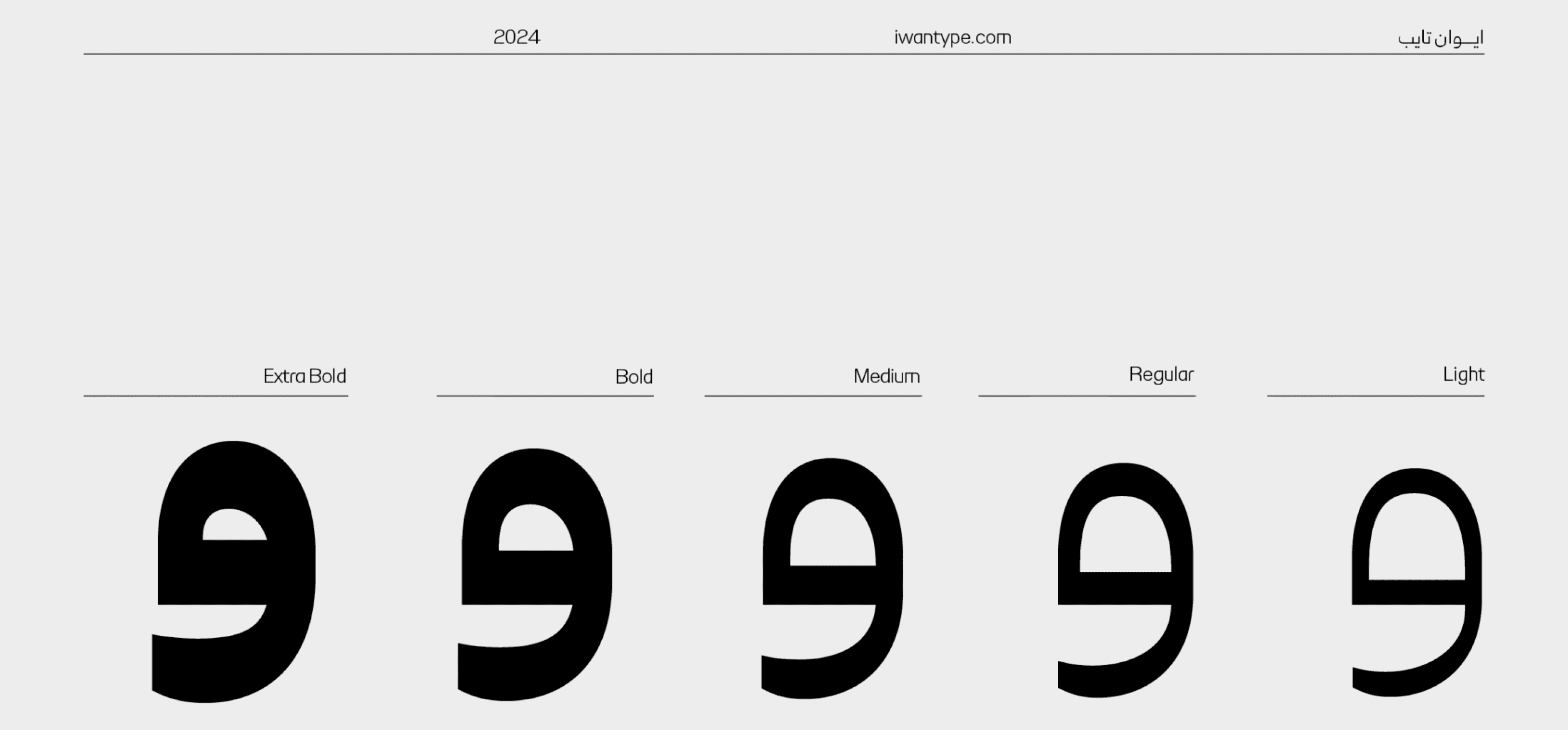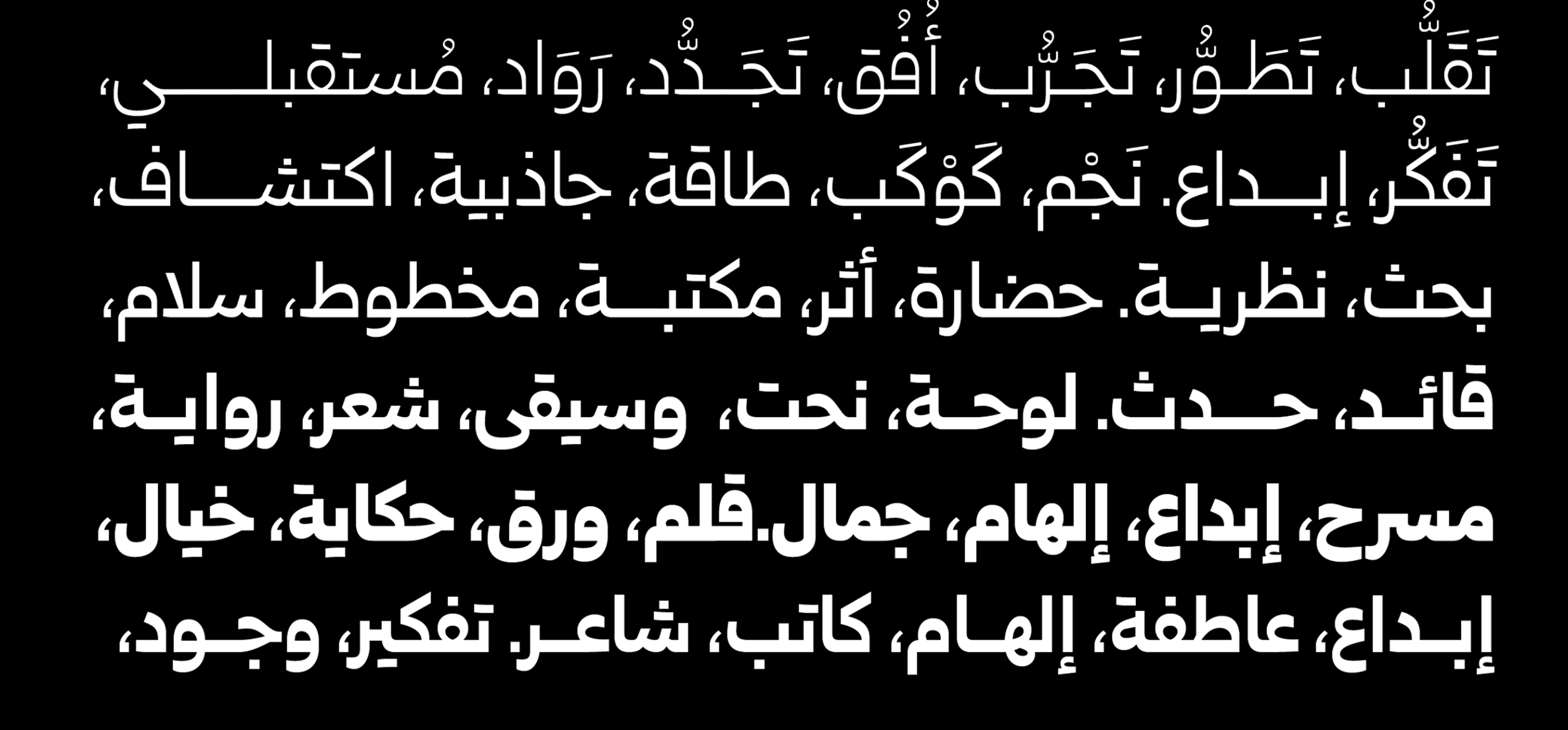
هو خط عربي فريد ومتميز، مستوحى من خط النسخ،يتميز بتصميم بسيط وانيق. ويمكن استخدامه في تصميم الجرافيك، والكتابة المطبوعة، والويب، والتطبيقات المحمولة.
مميزات خط غروب الطباعي:
تصميم بسيط وأنيق: يجمع الخط بين البساطة والجمالية التقليدية لخط النسخ، مما يجعله مناسبًا لمختلف أنواع التصميمات.
مزايـا OpenType: يتضمن الخط العديد من مزايا OpenType التي تضفي عليه مرونة وتنوعًا في الاستخدام، مثل:
الحروف المرسلة: لمسة تقليدية تضفي على النصوص جمالية خاصة.
حرف ياء بنزول أقل: يقلل من نزول السطر، مما يعزز من انتظام النصوص.
النقطة المستطيلة البديلة: توفر تنوعًا وجاذبية بصرية إضافية للنصوص.
الحروف المركبة: تسهم في تحسين المظهر العام للنص وتزيد من سلاسته.